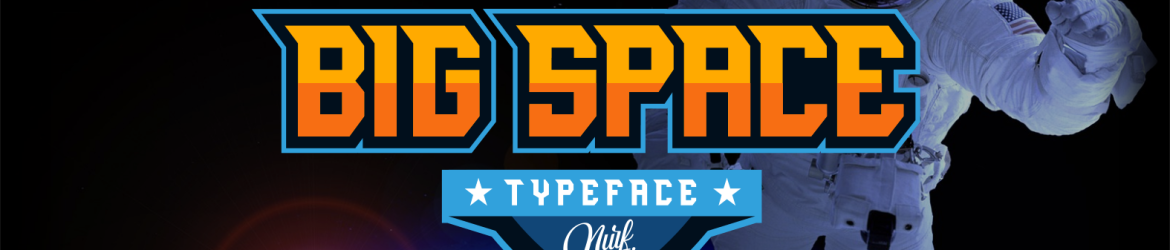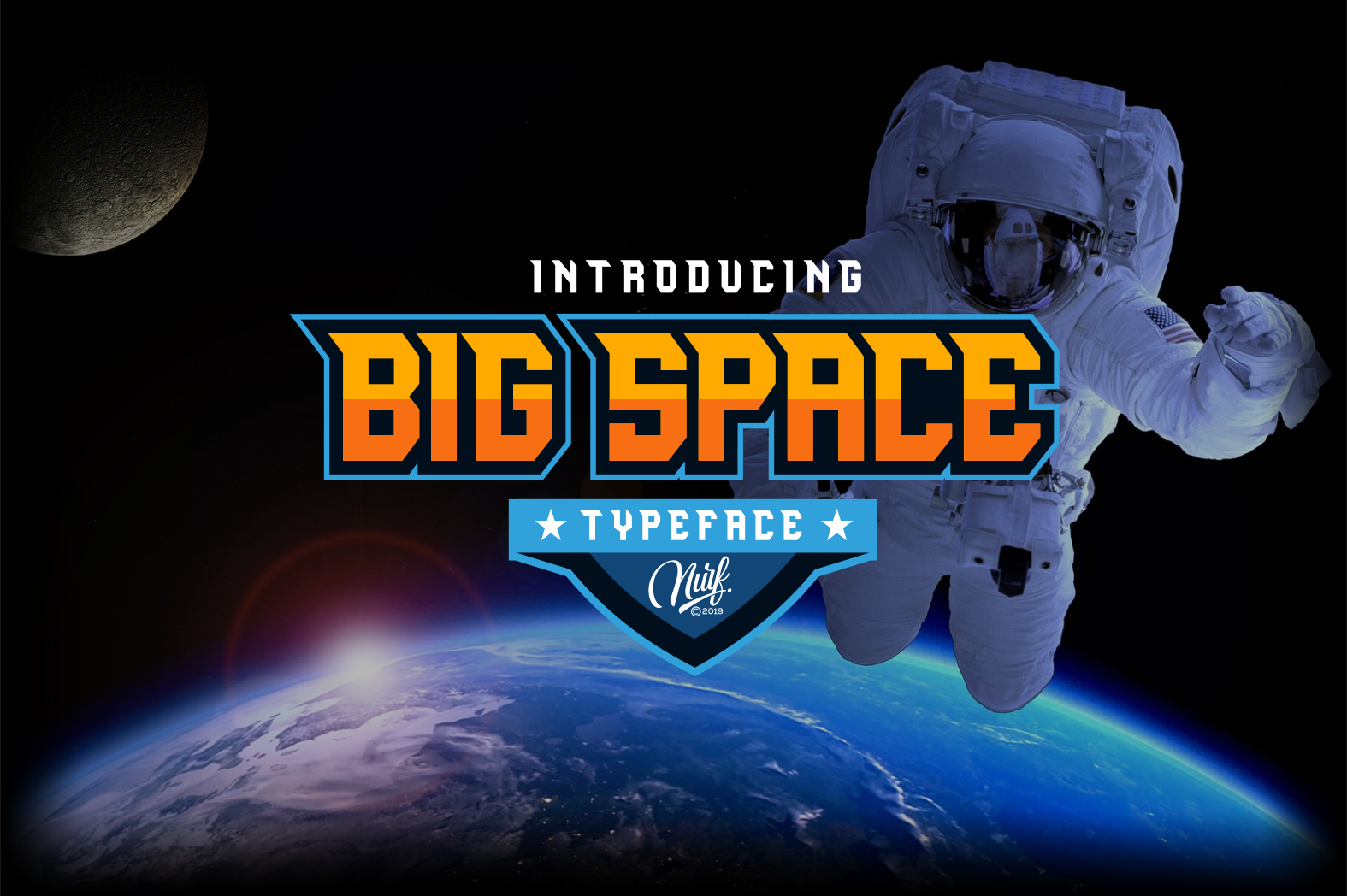
Big Space Typeface – Fonte Grátis
Big Space Typeface
A fonte ‘Big Space Typeface’ é perfeita para quem busca uma aparência chamativa e moderna. Criada no estilo esportivo, futurista e sci-fi, essa fonte exibe um visual bold e de ponta, ideal para uso em títulos, logotipos, mensagens publicitárias, números de camisa e até mesmo em cartazes. Ela se destaca pela sua simplicidade de uso e não dispõe de alternativas, tornando-a uma escolha prática e eficaz em qualquer projeto visual. Não há como negar que essa font oferece um toque moderno e audível para qualquer design que você possa criar. Para quem procura algo diferente e contemporâneo, este é um ótimo candidato para trazer o seu trabalho ao próximo nível.